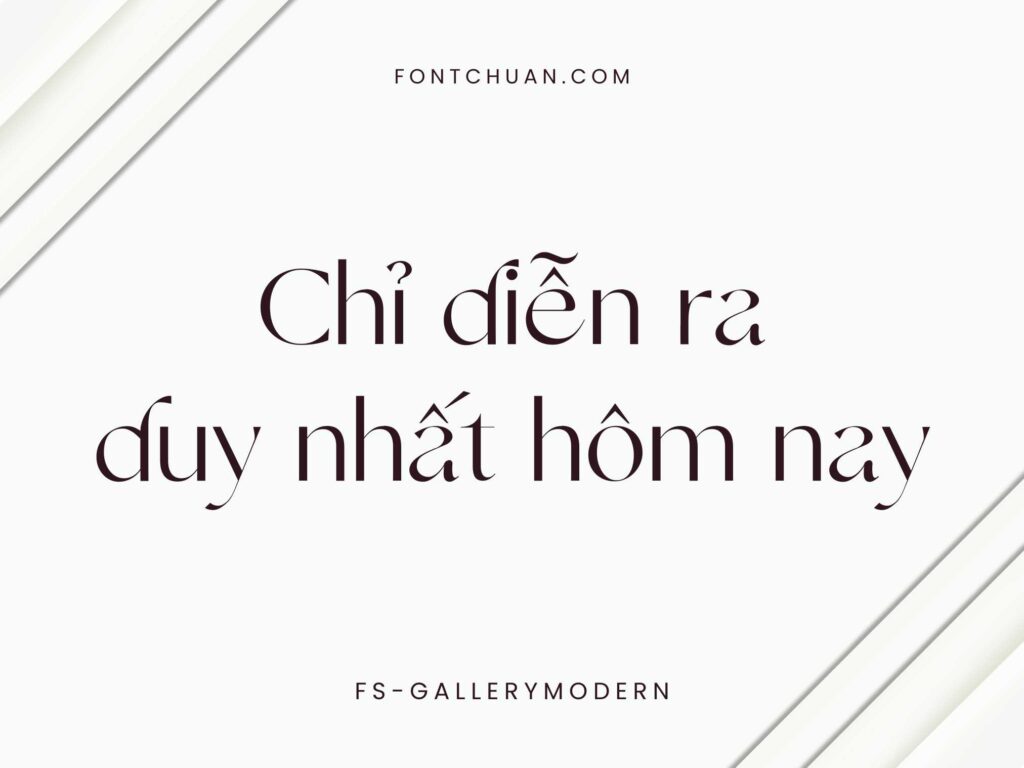
Font FS Gallery Modern Việt Hóa
Gallery Modern là một kiểu chữ hiện đại, kết hợp giữa các yếu tố cổ điển của serif và sự tinh tế của sans-serif, tạo nên một phong cách độc đáo và thu hút. Được thiết kế bởi New Tropical Design, font này nổi bật với các đường cong mềm mại và thân chữ uốn lượn, mang lại cảm giác thanh lịch và hiện đại. Với sự Việt hóa của Phông Chữ Việt, Gallery Modern hỗ trợ đầy đủ các ký tự tiếng Việt, giúp người dùng dễ dàng áp dụng trong các thiết kế đa ngôn ngữ. Thành viên của Font Chuẩn đã sưu tầm và chia sẻ font này nhằm đáp ứng nhu cầu của cộng đồng thiết kế.
Về đặc điểm thiết kế, Gallery Modern bao gồm đầy đủ chữ hoa, chữ thường, số và các ký tự đặc biệt, hỗ trợ đa ngôn ngữ. Font này đặc biệt phù hợp cho các dự án thiết kế như thương hiệu thời trang, thiết kế biên tập, logo và các ấn phẩm quảng cáo, mang lại sự sang trọng và tinh tế cho thiết kế. Ngoài ra, Gallery Modern cũng thích hợp cho các sự kiện như lễ hội, sinh nhật, Valentine và Trung thu, tạo không khí ấm áp và gần gũi. Trong lĩnh vực ngành nghề, font này được ứng dụng rộng rãi trong quảng cáo, thiết kế thiệp cưới, giáo dục và công nghệ, góp phần tạo nên sự độc đáo và thu hút cho các sản phẩm và thương hiệu.